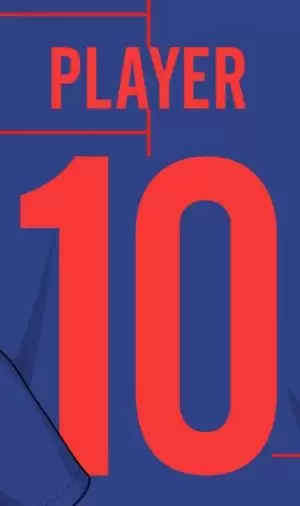
La Copa América de Brasil 2019 es el gran objetivo de las selecciones sudamericanas para este año. Tras la participación en la Copa del Mundo de Rusia 2018, en la cual ningún conjunto del continente llegó hasta las instancias finales, esta será la oportunidad para un buen resultado.
Con la llegada del torneo, las marcas que trabajan con los conjuntos nacionales se encuentran preparando los que serán los nuevos kits de juego. En el caso de adidas, la marca alemana que viste a la Selección de Argentina y de Colombia, se comenzaron a conocer las novedades de los diseños.
Uno de los principales cambios con respecto al kit 2018 estará en la tipografía. Con un diseño bastante rupturista para la Copa del Mundo de Rusia 2018, adidas llamó la atención. El estilo utilizado para las letras y números fue el cirílico y estuvo inspirado en la Unión Soviética. Los trazos característicos estaban hechos en 90 grados.
El nuevo estilo de letra para 2019 sería más moderno y tendría un estilo común en las letras y los números. Este diseño será exclusivo para los equipos sudamericanos que jugarán la Copa América, mientras que los equipos europeos, como Alemania, no tendrán novedades en su kit hasta más adelante.